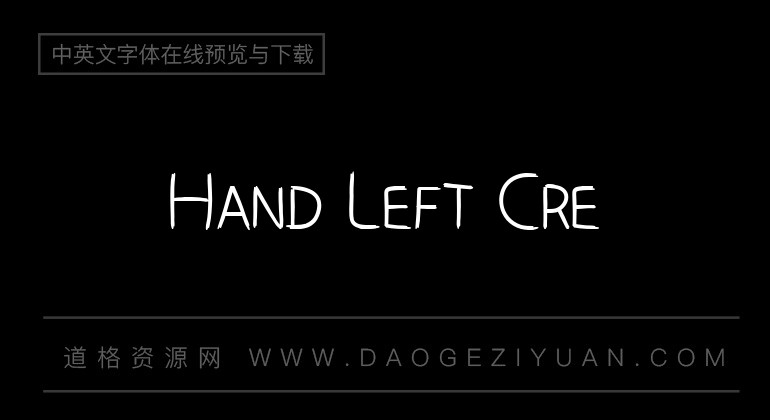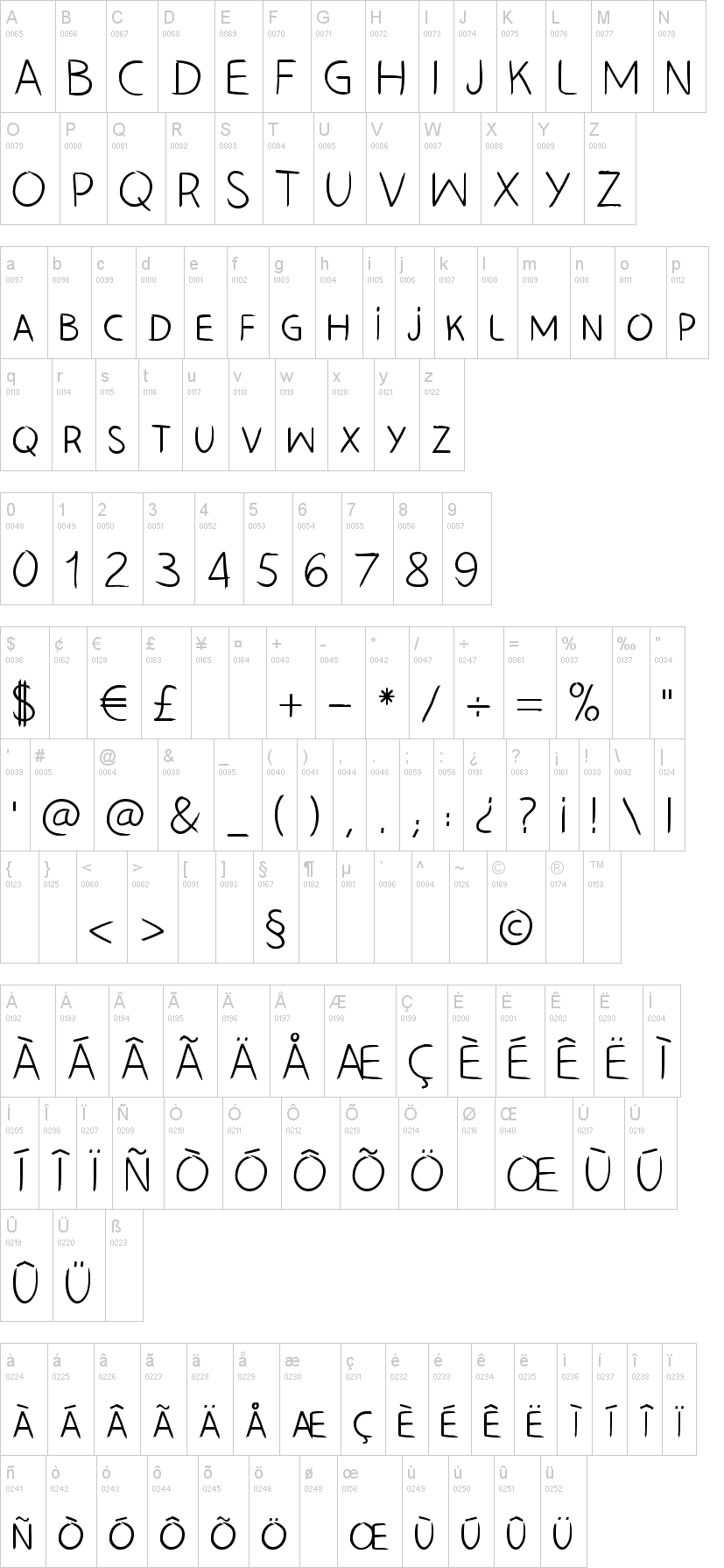
Hand Left Cre 字体是一款手写风格的英文字体,由英国设计师Alisa Nowak创作。这款字体具有自然、温柔、灵动的风格,细腻的线条及自然的曲线,使得它看起来更加温暖、舒适。它具有十分出色的可读性,使它成为印刷品、商标、标题等的首选字体。内容介绍
Hand Left Cre是一款非常不错的手写艺术字体,具有很好的视觉感,适合于文化类的宣传设计、商业类品牌的广告和产品包装设计以及个性化文字排版等较多场景。